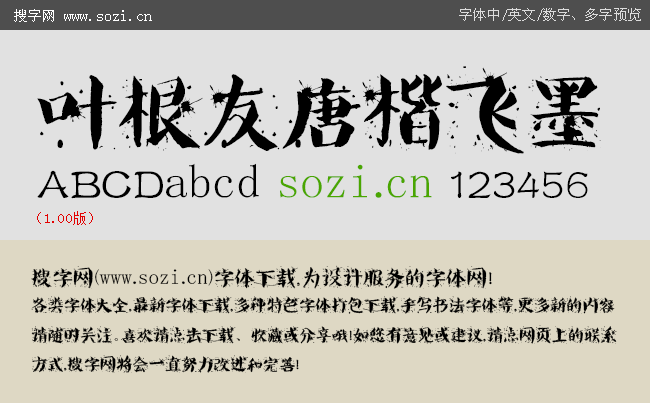
葉根友唐楷飛墨
搜字網(wǎng)給大家提供一款書法風(fēng)格的葉根友唐楷飛墨體下載。葉根友唐楷飛墨是在葉根友唐楷基礎(chǔ)上衍伸而來,增加了墨點的設(shè)計,該字體每一個字都帶有飛墨痕跡,筆鋒犀利,效果非常出彩,可用于卡通設(shè)計、廣告設(shè)計、平面設(shè)計、印刷包裝、報紙雜志等行業(yè)。